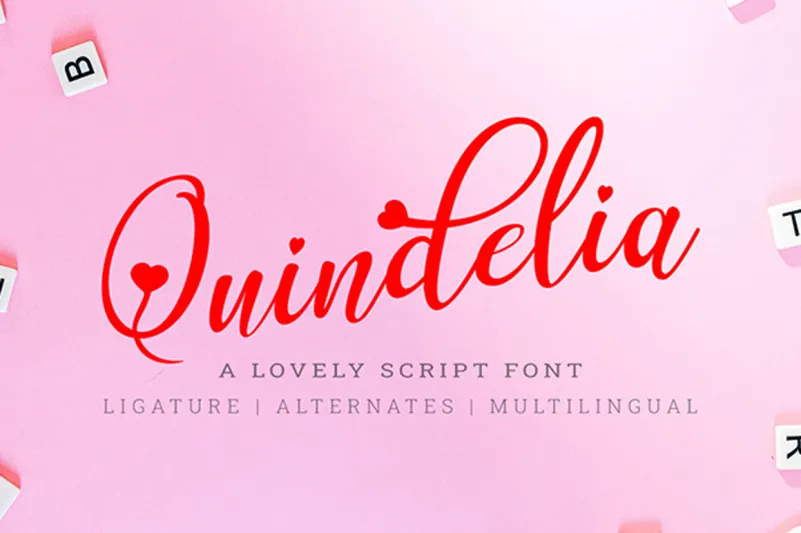
Quindelia Script Font – Download Grátis
A fonte Quindelia Script é uma excelente escolha para aqueles que buscam um estilo elegante e amoroso para suas criações digitais. Ela carrega consigo um toque especial de delicadeza, apresentando uma ligatura única e traços suaves e sofisticados. Esta fonte tem seis alternativas disponíveis, o que permite infinitas possibilidades na personalização e aplicabilidade. A Quindelia Font é perfeitamente adequada para um vasto número de projetos, desde cartões de aniversário até brochuras empresariais, passando por logotipos e desenhos gráficos. É perfeita para eventos memoráveis ou celebridades românticas – seja para criar uma identidade visual única ou adicionar um toque agradável à sua próxima criação. A Quindelia Font é definitivamente uma opção indispensável para designers digitais em busca de um efeito sofisticado e emocional.